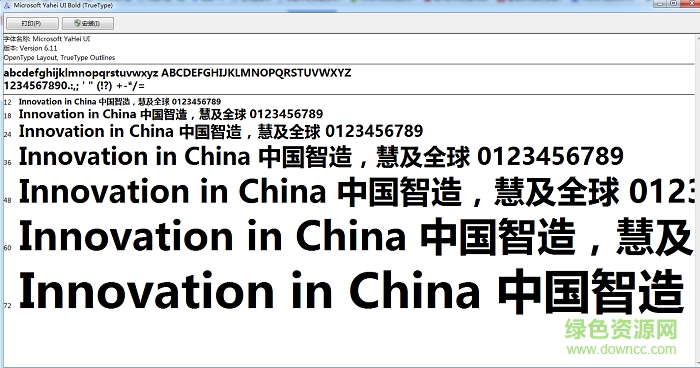
microsoft yahei ui bold/light
microsoft yahei ui 对应fonts里面的字体为微软雅黑改版字体,microsoft yahei ui粗体作出了一些改良,样式更美观,能更好地适应为win8和win10操作系统,有需要者欢迎在绿色资源网下载!
microsoft yahei字体介绍
雅黑,又称微软雅黑,是微软公司为其新一代操作系统Vista开发的中文字体,它是迄今为止个人电脑上可以显示的最清晰的中文字体。
microsoft yahei ui bold
microsoft yahei ui数字特点
“1”字的脚没了,顶上的衬线变弯了
“2”字的连接脚变弯了
“4”字的斜线变弯了
“5”字的直角变成钝角了
“7”字的脚变弯了
“8”字由一个圆拧成8字形变成两个圆相切了